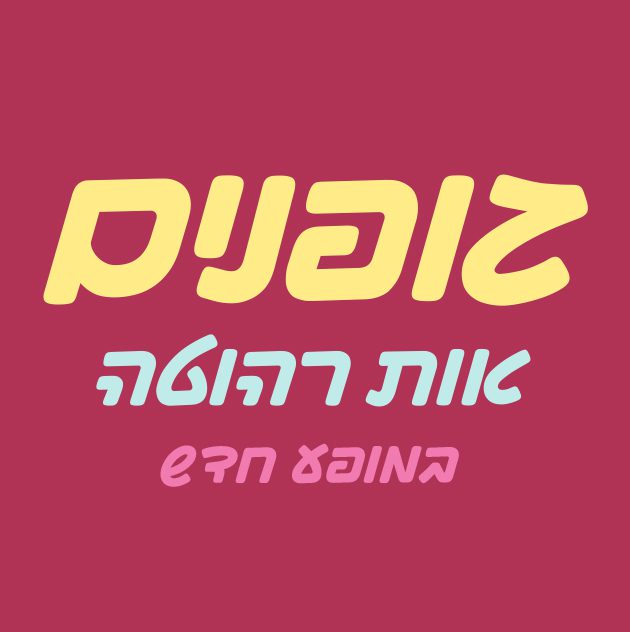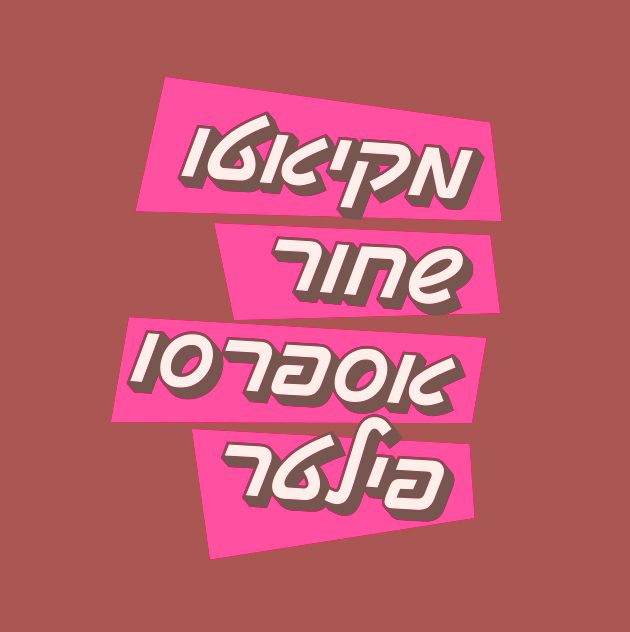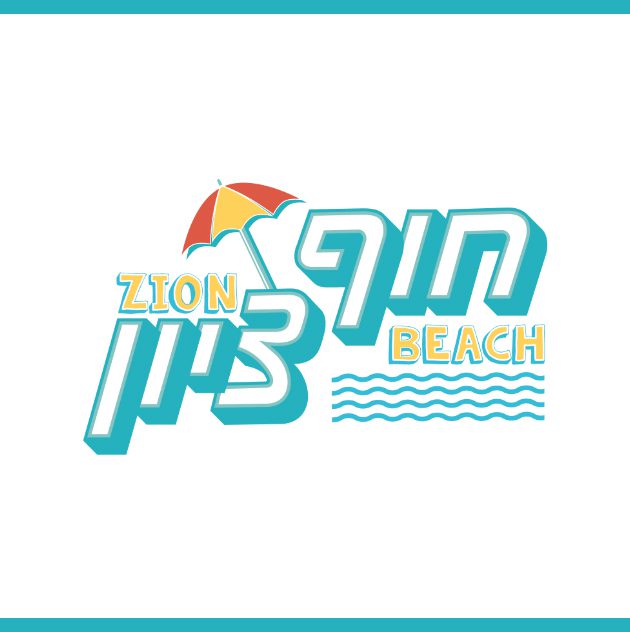
מקיאטו
מקיאטו / Fb Makiato
• שם הגופן:מקיאטו
• מעצב הגופן:נדב עזרא
• סגנון:רהוט
• קטגוריה: עברית ראווה
• מאפיינים: רגיל כבד 3-ד מילוי
• תכונות: אוונגרדי מגזיני מודרני מרובע מתוק נוסטלגי קשיח שמח
סיפור הגופן:
טיפוס האות מקיאטו הוא ללא ספק הסוכרייה שבחבורה. אות רהוטה שמרמזת על זרימה ומהירות הכתיבה, בעלת מבנה גוף ריבועי הלקוח מהמבנה של אות הדפוס. יחודיות האות מתבטא ביכולת המפתיעה שלה להחזיק גושי טקסט גדולים יחסית לפונטים אחרים בג׳אנר. מבחינתי העבודה על האות הייתה סוג של משחק כייפי וקליל. האות מגיעה במגוון משקלים ומתאימה בעיקר לעיצוב לוגו.